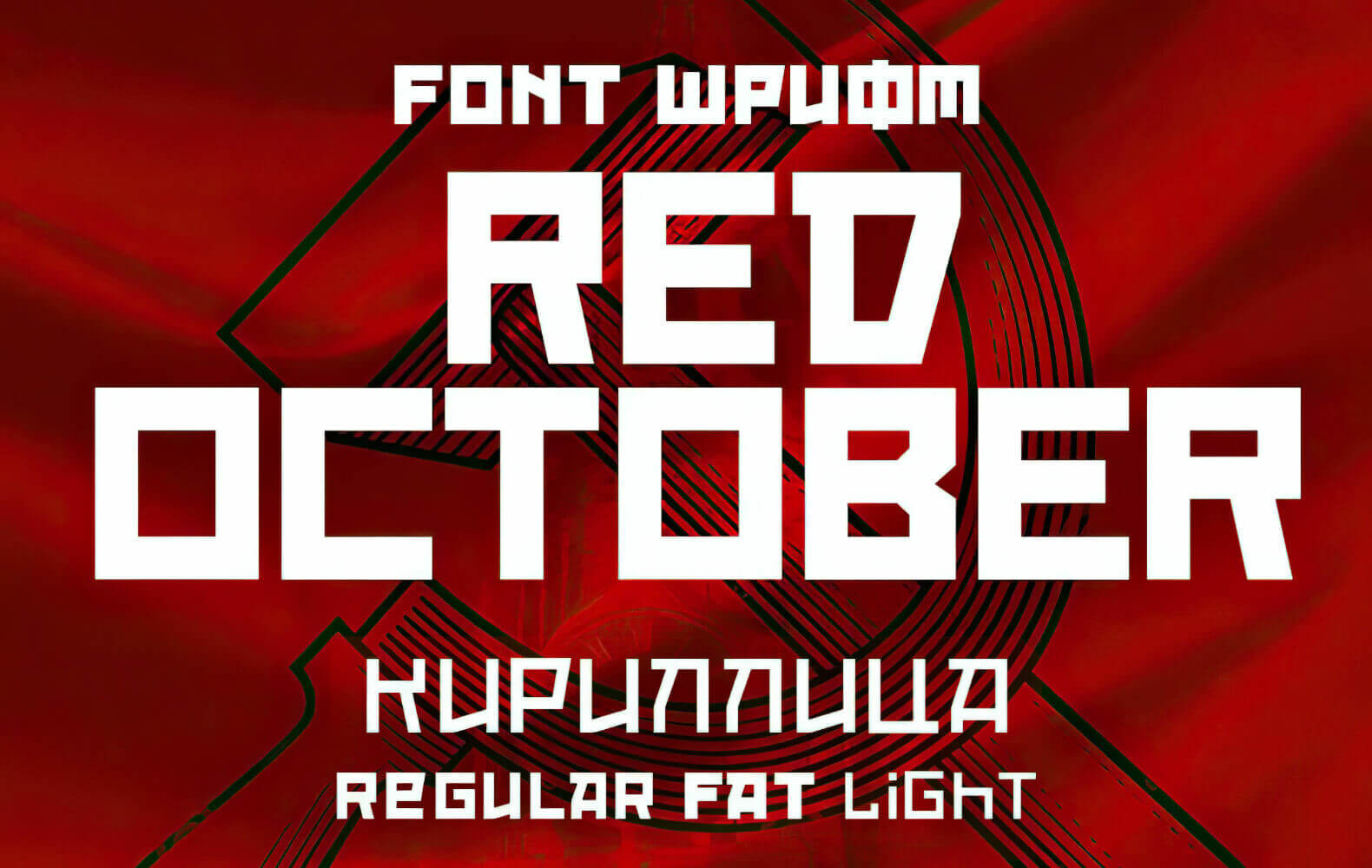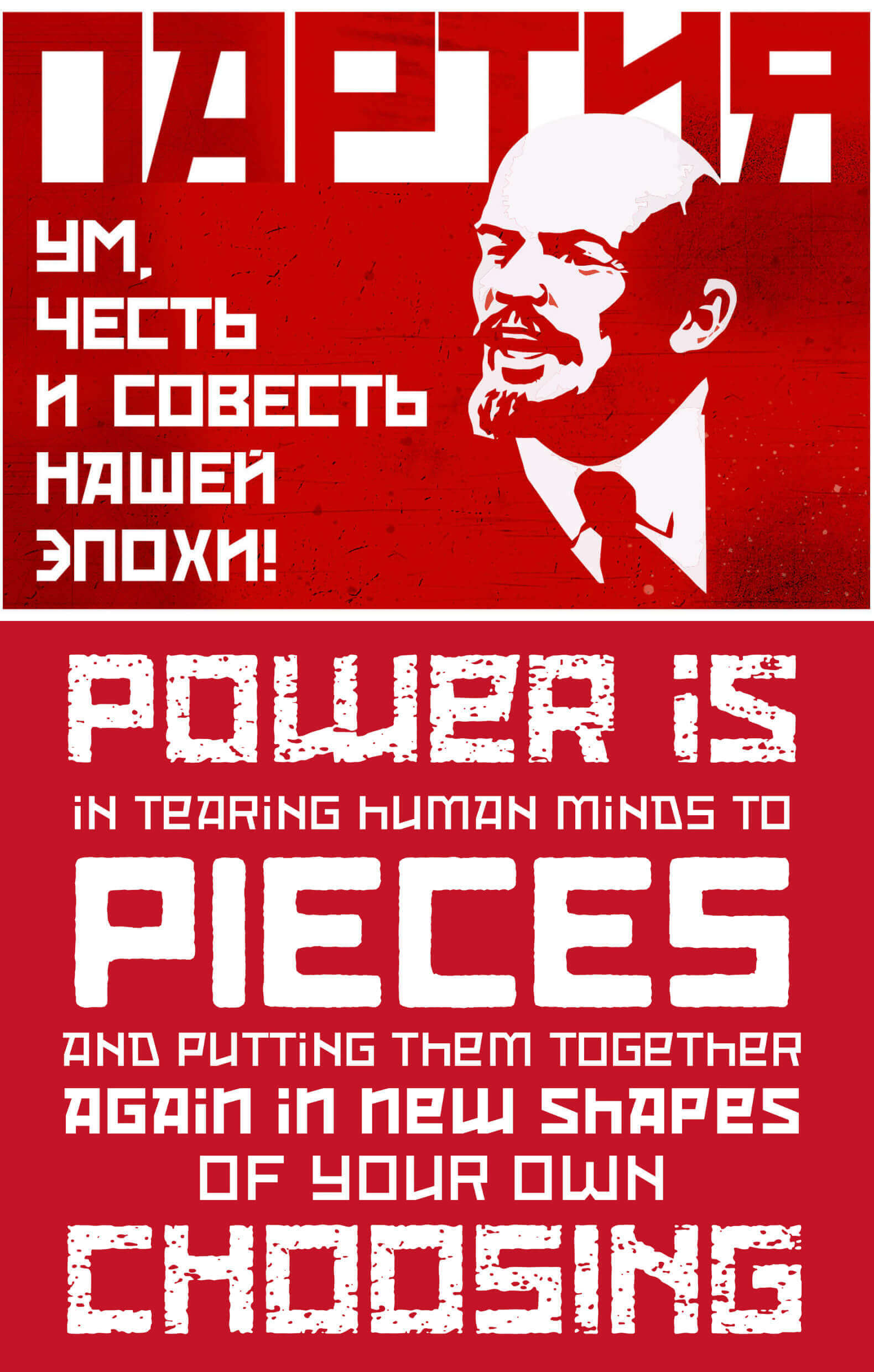
Шрифт — Red October (Кириллица/Латиница)
Red October – конструктивистский шрифт вдохновлен советскими пропагандистскими плакатами. Он стал довольно популярным, особенно в американских фильмах, таких как R.E.D, Die Hard 5 и Repo – The Genetic Opera, а также на обложке сингла Rihanna’s “Russian Roulette”.
Шрифт поддерживает только верхний регистр букв, имеет несколько начертаний (Regular, Fat и Light). С ним вы сможете писать на латинице и кириллице.
Т и Ё не печатает